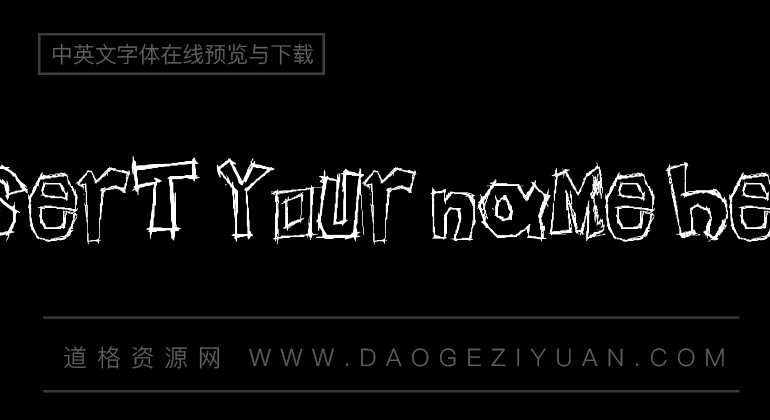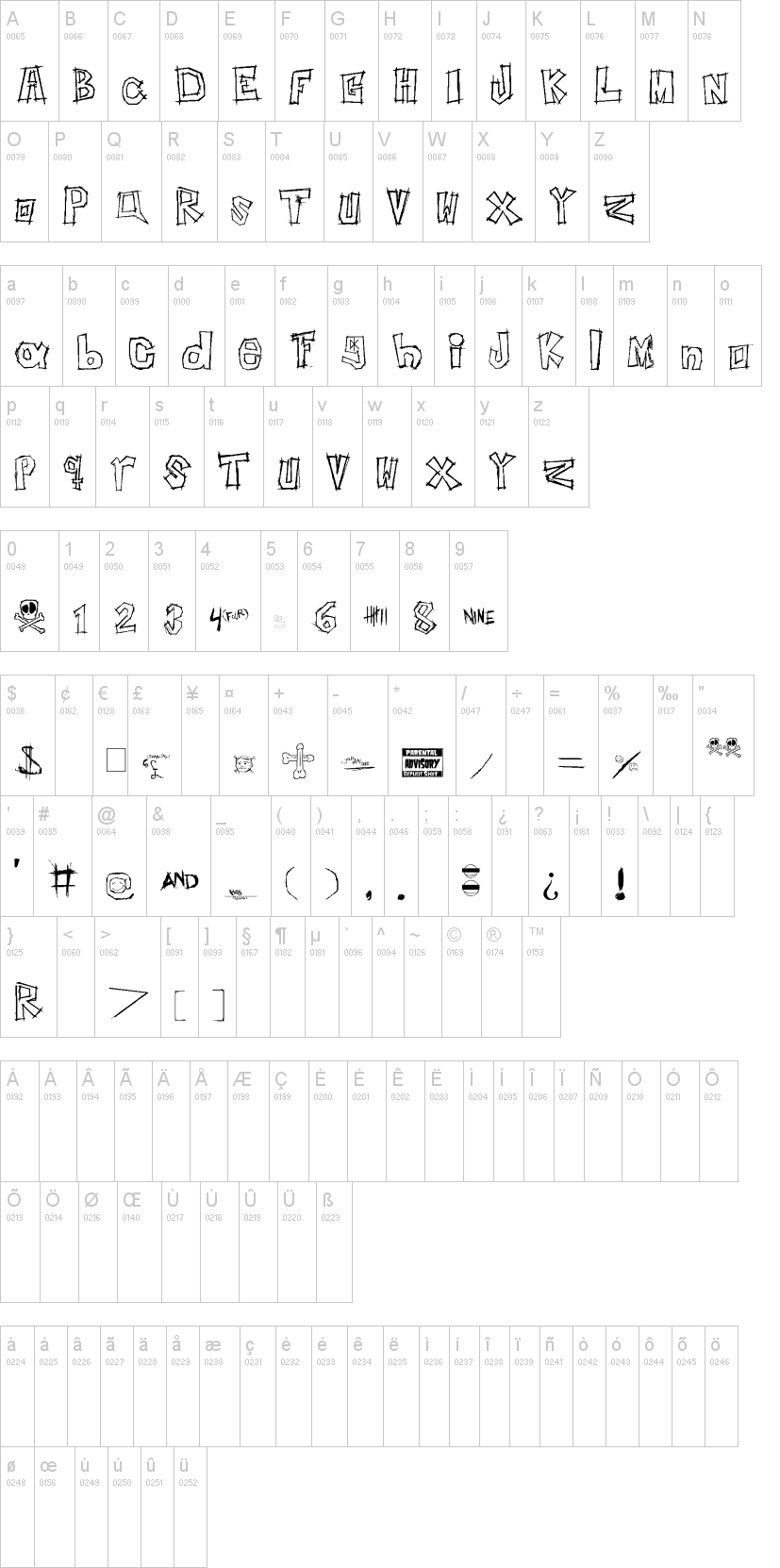
Insert your name here 是一款可以用来创建自定义名字的字体。它可以让你自由地设计自己的名字,以及其他任何你想要的文字,让你的文字更加个性化。它有多种字体样式可供选择,可以让你创造出属于自己的个性字体。它还具有容易使用,高效率,多种字体样式,调整字体大小等特点,可以让你更加容易地为自己的文字做出改变,从而让你的文字更加个性化。内容介绍
Insert your name here是一款非常不错的手写艺术字体,具有很好的视觉感,适合于文化类的宣传设计、商业类品牌的广告和产品包装设计以及个性化文字排版等较多场景。